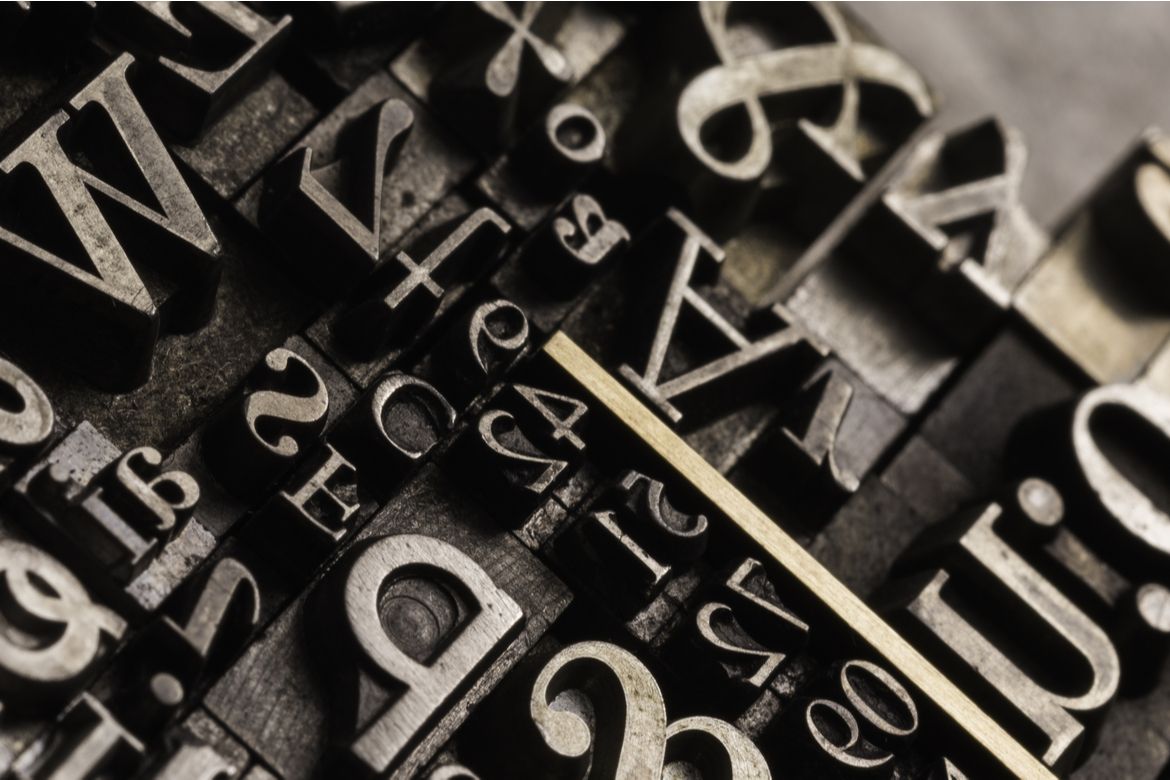
Come scegliere un font per i tuoi progetti editoriali?
Ecco alcune linee guida per capire come scegliere un font adatto al tuo progetto
Quante volte ti è capitato di essere indeciso sul font più adatto per il tuo progetto editoriale? Magari hai perso tempo provandone diversi, ma alla fine il dubbio di aver individuato quello giusto è rimasto. Come scegliere un font giusto per un progetto specifico? Ci sono delle regole da seguire? Delle linee guida ovviamente esistono e questo articolo ha lo scopo di chiarirti le idee sull’argomento.
Se riesci a capire come scegliere un font, non avrai più alcun problema ogni volta che predisporrai un progetto da mandare in stampa, qualunque esso sia. Il font è una parte molto importante del processo creativo e svolge un ruolo rilevante nella buona riuscita di uno stampato.
La differenza tra serif e sans-serif
Possiamo dividere i font in due macroaree con caratteri:
• serif (con grazie) che si ispirano alla scrittura manuale, rendono agevole la lettura di lunghi testi e per questo vengono scelti per libri, riviste, quotidiani.
• sans-serif (senza grazie), sono semplici e lineari, senza appendici. Si usano in ambito pubblicitario o per i testi per bambini.
La leggibilità del font: ecco da cosa dipende
Il font deve innanzitutto essere coerente con il messaggio che si intende trasmettere e quindi in linea con il testo. La prima domanda che devi porti prima di scegliere un font è quale effetto vuoi stimolare nell’osservatore. È poi necessario valutare fattori oggettivi quali la leggibilità, che è strettamente legata allo spessore del carattere e con la sua struttura grafica, con gli spazi e l’interlinea.
Un font calligrafico o decorativo come Blackradder è bello da vedere, ma poco leggibile. Questo perché è progettato per attrarre lo sguardo alla prima occhiata, è quindi indicato per frasi e testi brevi, ma non per testi lunghi come può essere un libro o un articolo di giornale per i quali un font pulito come il Verdana o l’Arial sarà invece la scelta migliore.
In linea generale se hai bisogno di un font che sia leggibile devi optare per quelli che hanno forme più convenzionali, ricordando anche di lasciare una buona spaziatura perché le lettere troppo vicine rendono più lenta la lettura.
Ad ogni progetto il suo font
Vediamo quindi come scegliere un font in base al progetto. Il font deve rispondere anche alle aspettative estetiche del target di lettori. Per un progetto di lavoro o per la stampa di una brochure informativa di un’azienda, che mira a distinguersi per affidabilità è meglio scegliere font eleganti come: il Minion Pro, il Caslon o il Bembo. Il famoso Comic Sans è invece tra i più amati dai creativi. In alcuni casi la scelta giusta può essere quella di accostare due font diversi per i titoli e per i paragrafi.
Quindi, come scegliere il font giusto?